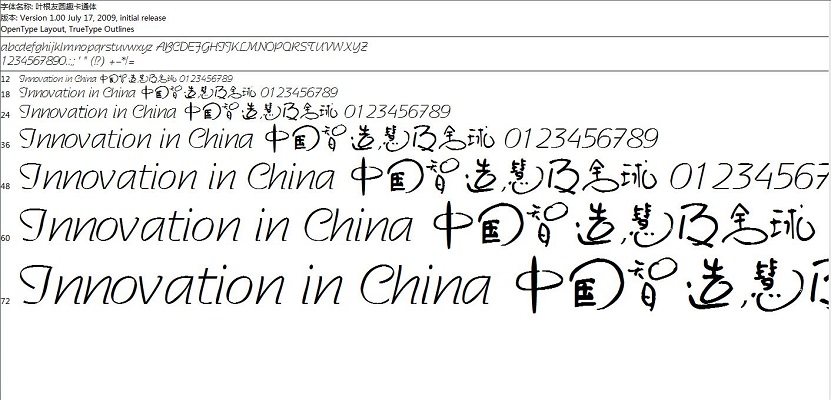
葉根友圓趣卡通體是一款看起來非常卡通,非常有趣的字體,非常適用于關(guān)于兒童的一些教學(xué)海報等相關(guān)文案,也可以作為廣告語的宣傳字體,感興趣的朋友們快來下載吧!
葉根友圓趣卡通體該字庫為2009年6月最新設(shè)計開發(fā),為書法家葉根友先生親自設(shè)計書寫的原創(chuàng)手寫字體,類似于卡通體的風(fēng)格,整個字形生動活潑,跳躍自然,大膽創(chuàng)新筆畫結(jié)構(gòu)是該字庫的主要特點,適合用于廣告語,兒童海報設(shè)計以及其他比較追求時尚、生動主題的平面或動態(tài)媒體中。